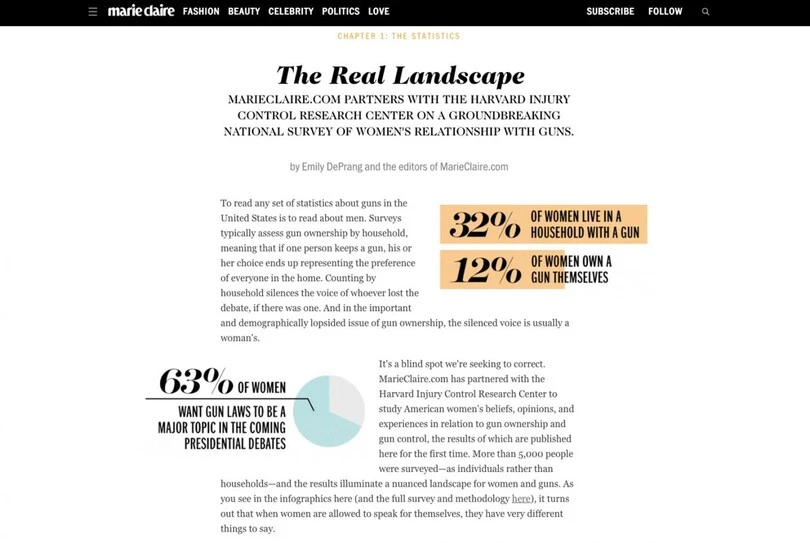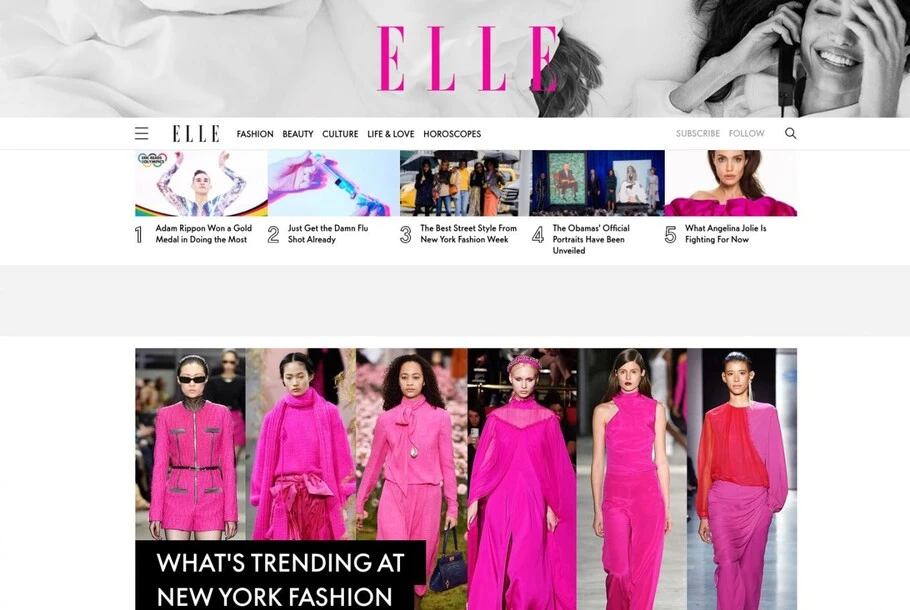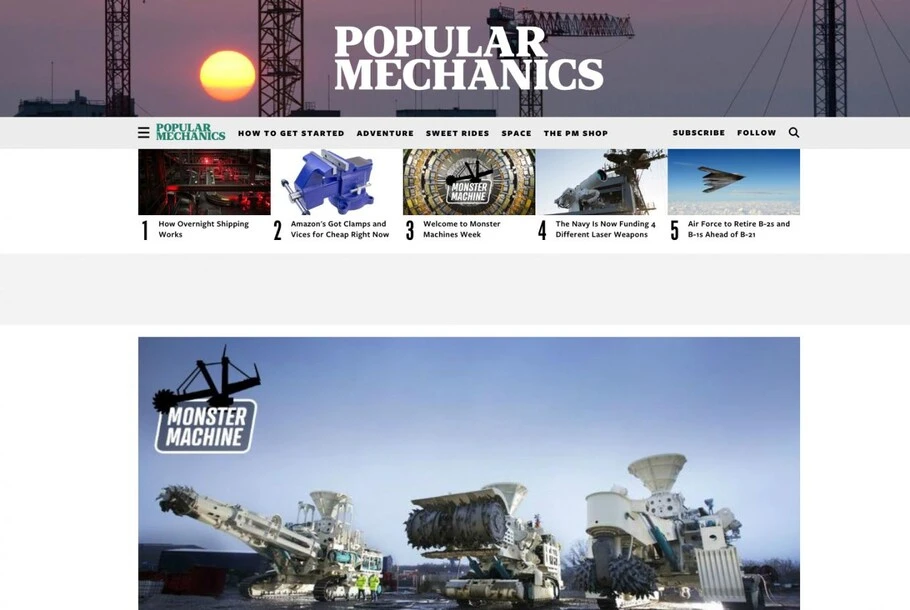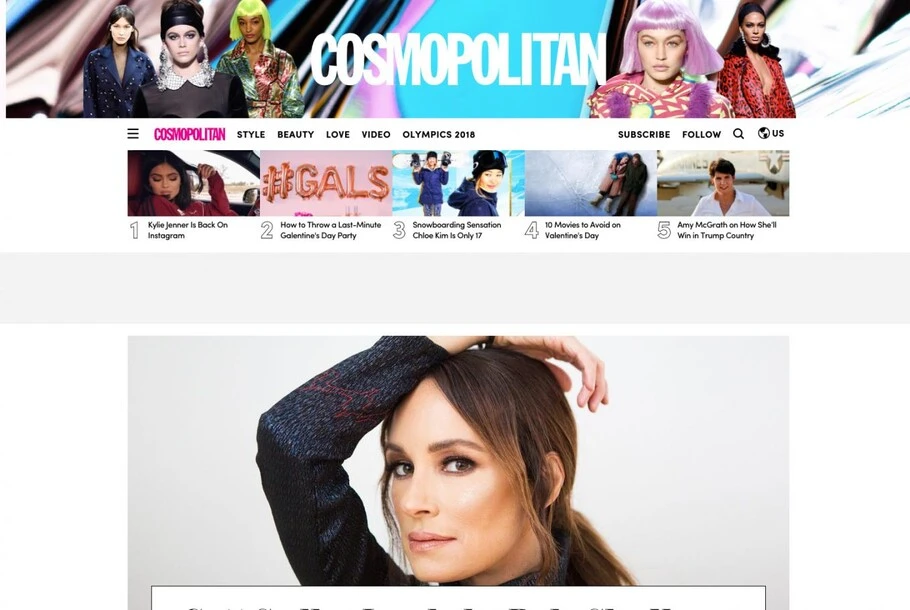
赫斯特杂志数字媒体的创意自由与数字灵活性。
“ 跨渠道拥有一致的视觉品牌很重要。Mosaic提供的广泛选择有助于我们做到这一点。 ”
赫斯特(Hearst )成立于1887年,是美国最受推崇的媒体机构之一,旗下拥有数十家标志性的报纸和杂志。但像赫斯特这样的公司,如果没有适应和成长的意愿,是撑不了这么久的。
对赫斯特杂志来说,适应意味着走向数字化。在过去的十年中,杂志部门不断发展,以满足不断增长的在线受众的需求。Monotype存在于每一个步骤中。
新数字现实
“与十年前相比,我们在数字体验方面拥有更多的自主权,”赫斯特杂志数字媒体(HMDM)的用户体验和产品设计创意总监Theresa Mershon表示。考虑到赫斯特杂志的一些杂志几十年来一直在书架和杂志架上盯着我们,这就说明了很多问题。
HMDM产品组合中的18个品牌,包括ELLE.com、Esquire.com和cosmopolitan,目前都使用Monotype字体和技术。2009年左右,Mershon的团队开始将这些杂志转换为web字体,以优化面向数字受众的网站。
web字体对于高效的响应式设计至关重要,在该设计中,网页会自动缩放以适应不同的屏幕尺寸,而不会降低读者的体验。对于HMDM来说,使用web字体意味着无论受众使用他们的手机、台式机还是平板电脑,内容都会清晰易读。
但web字体仅仅是个开始。
不断发展的在线体验
仅仅在线复制打印体验并到此为止是不够的。数字用户的要求越来越高,新设备不断进入这个领域,出版商也必须跟上步伐。虽然这看起来压力很大,但事实是,只要数字出版商能够胜任这项任务,他们就有几乎无限的机会来改进产品和业务。
HMDM接受了这一挑战,并将其数字品牌转移到了一个围绕速度、简单性和适应性设计的新平台上。每个网站都使用相同的底层结构,这使得Mershon的团队能够快速迭代新想法。
“我们需要灵活性,以适应受众与我们接触的方式的变化,”Mershon表示。“该系统具有很强的可扩展性,使我们能够真正做到敏捷。”
字体对于使此系统正常工作至关重要,因为没有它们,每个网站实际上都是相同的。“我们确实需要使用字体和颜色来建立每个品牌的标识,”Mershon表示。
HMDM使用Monotype的Mosaic™服务,这给了Mershon的团队试验新想法的自由。“我们可以为高价值的新闻工作制作精美的演示文稿,”Mershon表示。她的团队开发了利用Monotype web字体的半定制模板,让她的设计师可以自由地创作受众喜欢的内容。
“ “我们确实需要使用字体和颜色来建立每个品牌的标识。” ”
对性能痴迷
一个完美的品牌网站是必要的,但如果网站需要很长时间才能加载,那就不值得了。这没有让Mershon或她的团队迷失方向。
”我们采用全面的设计方法。我们的设计师端到端地工作,并深入了解他们可以改变什么,以及这些变更如何影响页面性能,”Mershon表示。“除此之外,工程人员还不断迭代以提高页面速度。”
A bespoke long-form article; working with Monotype allows HMDM to be flexible with its platform, opening opportunities for creative freedom while ensuring pages load quickly and smoothly.
与Monotype合作,使不断测试和提高页面性能变得非常轻松。Mershon说,Monotype独有的一个关键好处是,Monotype web字体看起来很棒,加载速度也很快。当每一刻都很重要的时候,这一点至关重要。而且,拥有灵活的许可证意味着可以测试的内容几乎没有限制。
“我们的目标是在不影响性能的情况下尽可能拥有最美观的页面体验,”Mershon表示。“Mosaic让我们能够迅速切换我们正在做的事情。”
展望未来
如果说数字时代有什么真理的话,那就是变化是唯一不变的。Mershon指出,虽然从印刷到数字平台的转变是巨大的,但这并不是故事的结尾。
“随着我们的品牌在许多平台上找到自己的受众,视觉识别会扩大和改变关注焦点,”她表示。“比如,《Cosmopolitan》在Snapchat上的形象可爱、有趣且非常活泼,而《Cosmopolitan》在Instagram上的形象往往更加时尚、漂亮和简约。”
“在不同的渠道之间拥有一致的视觉品牌非常重要,”Mershon表示,“但关键是要同时拥有这两种身份,并在特定的渠道上呈现任何吸引观众的一面。Mosaic提供的广泛选择有助于我们做到这一点。”
字体对于达到这种平衡至关重要,因为它可以让品牌在不失去基本视觉联系的情况下改变自己的声音。这意味着,即使实际体验在不同的渠道之间有巨大的不同,受众也始终知道这仍然是《Cosmopolitan》的话语。
“ “在不同的渠道之间拥有一致的视觉品牌非常重要。Mosaic提供的广泛选择有助于我们做到这一点。” ”
与Monotype合作,使Mershon能够专注于为HMDM的受众提供最佳的体验。她的团队不必担心什么字体可以使用,什么字体不能使用,他们可以放心地迭代、实验和优化,因为知道字体会正常工作,并且会运作得很好。
或者,正如Mershon所说,“我们的许可证让我们可以无忧无虑地发挥。”